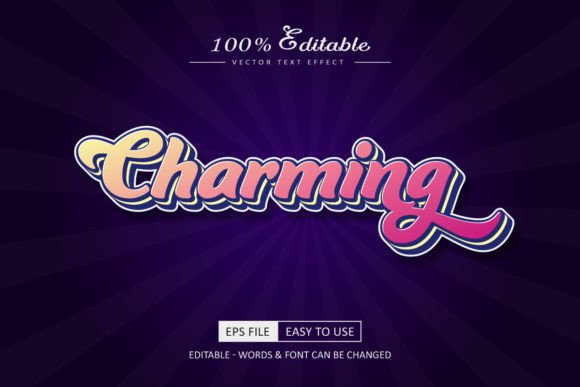
Charming Text Effect Font Style
Trouver les bons éléments de conception peut être un défi, mais Charming Text Effect Font Style propose une collection exceptionnelle qui rehausse instantanément votre travail.